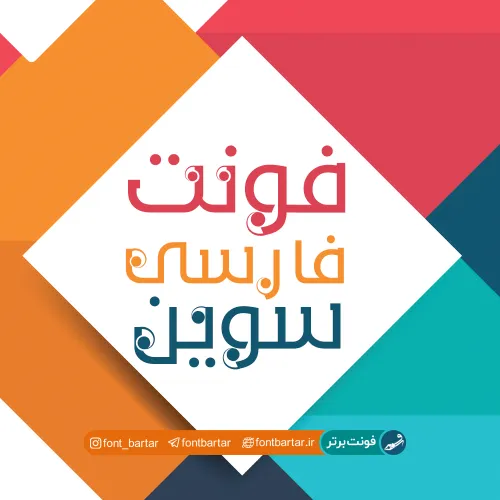
فونت فارسی سوین
فونت فارسی سوین با ساختار پیچیده و تلفیق شده با عناصر اورنامنت که به واسطه درست بکار رفتن این عناصر بسیار یکدست و زیبا خروجی می دهد فونت فارسی سوین  خاص فارسی مناسب طراحی است و جزو فونت های فارسی گرافیکی و مناسب تایپوگرافی دسته بندی می شود ، این فونت نسخه رایگان فونت اصلاح شده عربی جدید و خلاقانه است که توسط هاشم شهرزاد به فارسی تبدیل شده می باشد که (دارای حروف گچ ، پژ و حروف انگلیسی و اصلاح نقطه ها و … ) می باشد.
فونت سوین مورد استفاده برای:
• طراحان وب سایت و گرافیست های خلاق می توانند از این مجموعه زیبا فونت در طراحی پروژه های تبلیغاتی و تجاری خود کمک بگیرند.